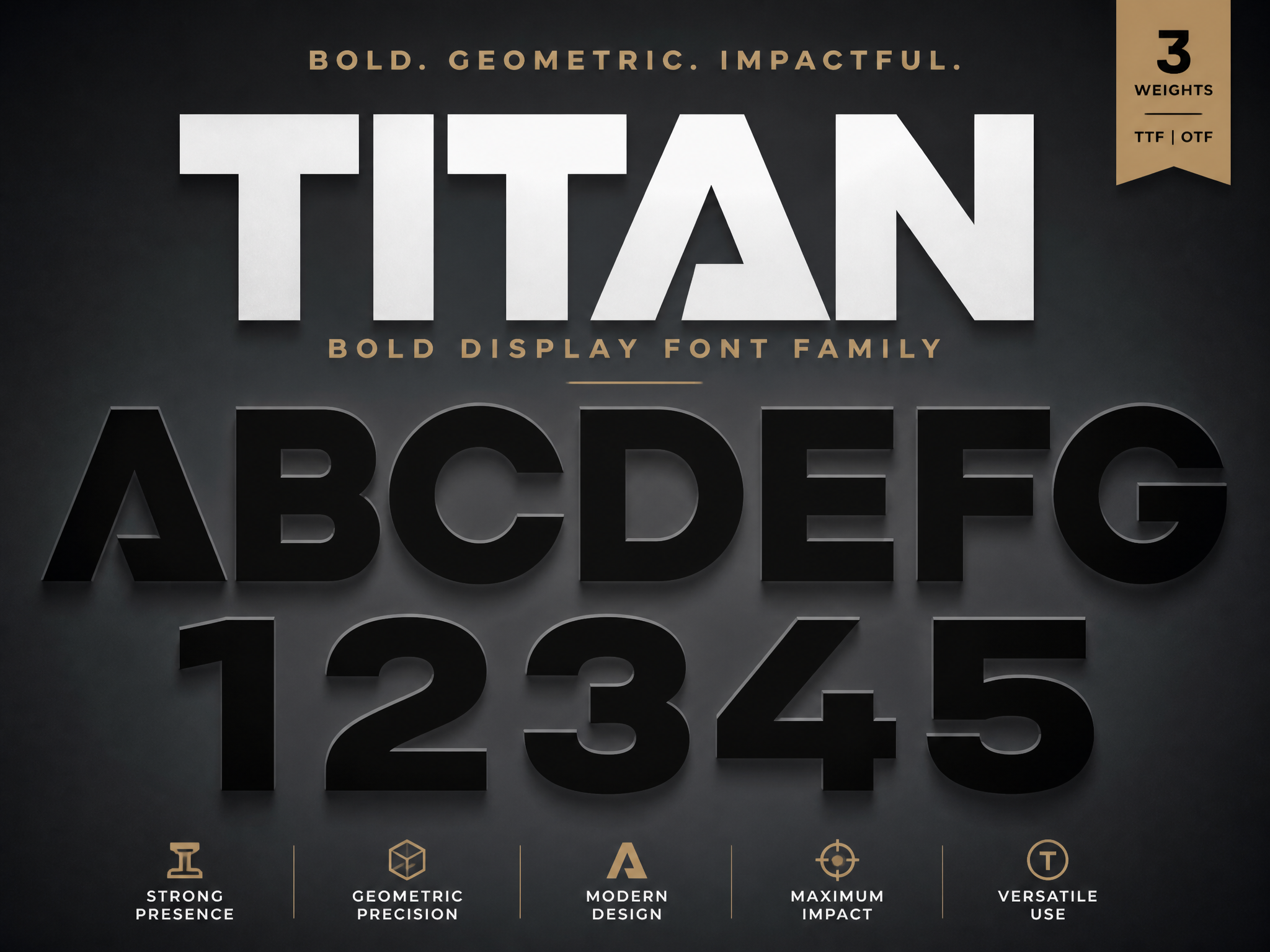
Başlık & Poster Font Ailesi; afiş, poster, kapak ve büyük başlıklar için tasarlanmış güçlü karakterlere sahip bir display font koleksiyonudur. Dramatik harf formları ve güçlü kalınlık kontrastıyla her ortamda göz alıcı bir etki yaratır. Aile; Regular, Bold ve Black ağırlıklarını kapsar. İçerdiği dekoratif alternatif harfler ve bağlantı karakterleri (ligature) sayesinde sıradan bir metnin bile özel bir tasarıma dönüşmesini sağlar. Tüm Türkçe karakterler eksiksiz desteklenir. OTF, TTF ve WOFF formatlarında teslim edilir. Logo, reklam, afiş ve marka projeleri için mükemmeldir; ticari kullanıma uygundur.
Başlık & Poster Font Ailesi